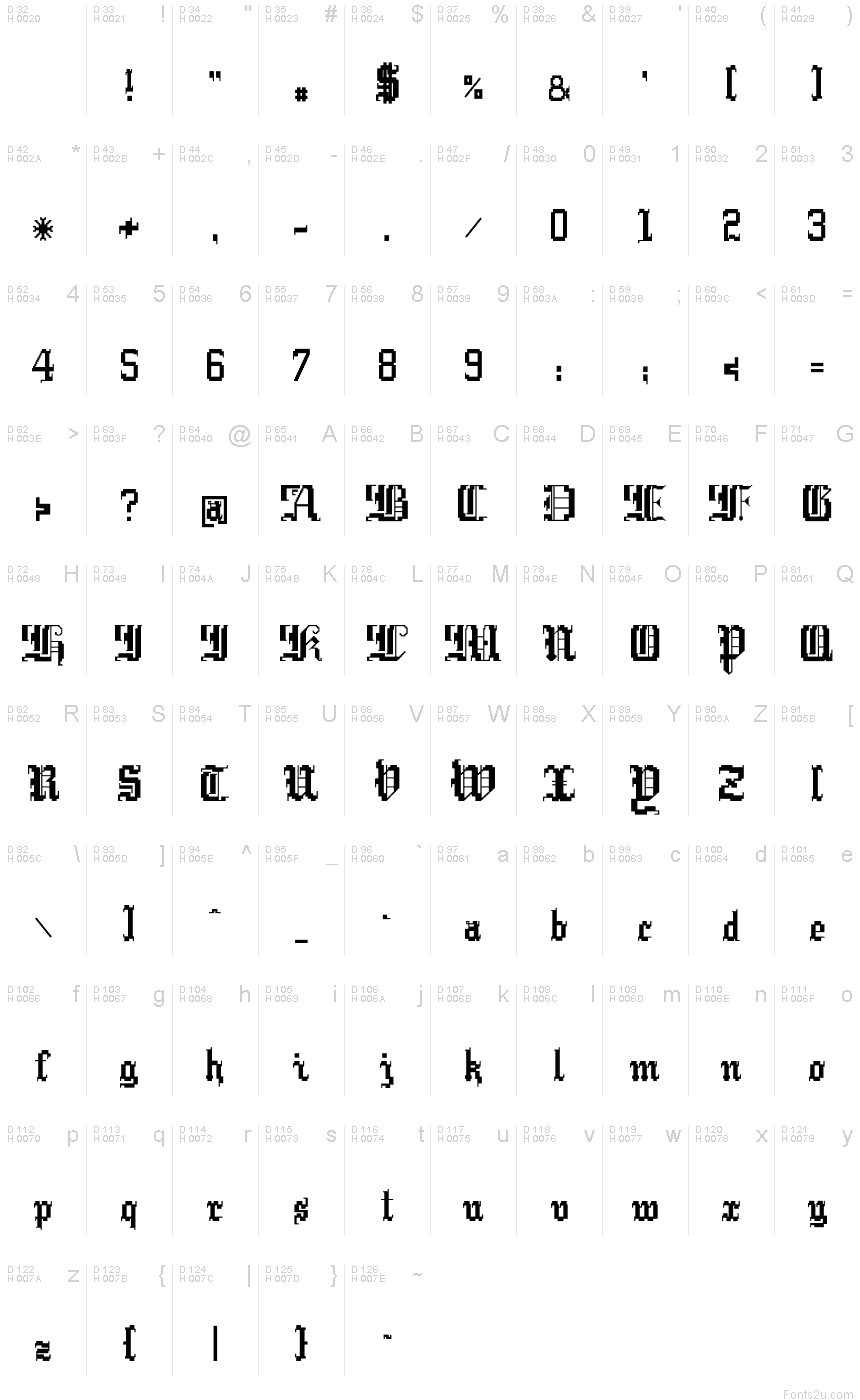
Argor Cwar Scaqh di JP Mallaroni è un carattere bitmap gotico gratuito che fonde griglie di pixel affilate con un dramma medievale. Ogni lettera sembra scolpita nella pietra nera e incastrata in una robusta cornice a 8 bit: angolare, compatta e leggermente minacciosa, con un ritmo costante che rimane leggibile anche in dimensioni ridotte. Il risultato è una texture retro d'atmosfera che appare nitida sugli schermi moderni.
Con Argor Cwar Scaqh, puoi dare ai titoli dei giochi, alle interfacce dei dungeon, agli overlay per stream fantasy, ai loghi delle band metal, ai poster e alle fanzine horror una voce oscura del vecchio mondo con un fascino pixel inconfondibile. Questo carattere gratuito brilla soprattutto se usato in grandi dimensioni per titoli e badge; abbinalo a un semplice font pixel monospaced per i menu o il corpo del testo per mantenere la leggibilità, lasciando che il titolo esprima tutta l'attitudine gotica.